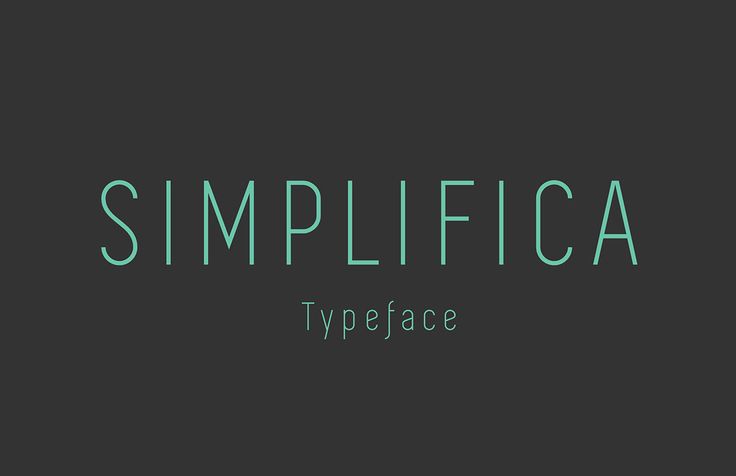
Бесплатные легкие шрифты для загрузки
В этой статье вы найдете подборку бесплатных тонких шрифтов, которые вы можете загрузить и использовать в своих проектах.
При создании дизайна вы можете передать определенное настроение или заявить о себе с помощью выбранных вами элементов дизайна, а также используемых с ними шрифтов.
Когда вы используете тонкие современные шрифты, ваш дизайн становится более привлекательным, и ваши зрители заманиваются сообщением, которое вы пытаетесь продать.
Однако у вас есть миллионы тонких шрифтов, от тонких шрифтов с засечками до тонких шрифтов без засечек, и выбор лучших тонких шрифтов для вашего конкретного проекта может стать проблемой.
В настоящее время вы заметите рост использования тонких шрифтов, и многие дизайнеры согласятся, что использование тонкого шрифта в их проекте идеально дополнит их идею.
Какие светлые или тонкие шрифты мы обсуждаем?
Основным ответом на вопрос «что такое светлый шрифт» будет шрифт, который светлее, чем римская версия шрифта, тогда как римская версия является простой, книжной или обычной.
Учитывая, что это довольно большой спектр, легким шрифтом считается тот, который использует меньший вес, чем обычный шрифт, и при неправильном использовании такой шрифт затрудняет чтение. Однако при правильном использовании это может быть очень полезно. Возможность неправильного использования отпугивает многих дизайнеров, которые предпочитают не использовать их.
Open Sans Condensed
Fonto Font Fonti Family
ARSENAL
Milano
AFTA SANS
Dosis Font Family
20020 EXISTENCE LIGHT
Quarterly BRK Font Family
CICLE
Rajdhani Font Family
RALEWAY
Web Serveroff Font Family
LANE
Labtop Font Family
ПЕЧАТЬ ЧЕТКО
Drugs Font
QUICKSAND
Tartlers End Font
WALKWAY
Fortheenas_01 Font Family
CAVIAR DREAMS
Josefin Sans Font Family
SOFIA PRO
Titillium Web Font Family
What is considered good use?
Легкий шрифт или тонкий шрифт может принести большую пользу, и вы можете получить бесплатные тонкие шрифты в Интернете, их много.
При правильном использовании они дают четкое и четкое изображение, но если не работает хотя бы одна вещь, текст довольно сложно читать, что еще хуже для потенциальных зрителей, у которых могут быть проблемы со зрением.
Плюсы использования светлых шрифтов
Светлый шрифт может обеспечить контраст, который отличает ваши заголовки от остального текста. Когда у вас нет этой дифференциации, между ними очень легко может возникнуть конфликт. Изменить размер заголовка и текста не всегда достаточно, и вам может потребоваться внести дополнительные изменения.
Здесь вступает в действие светлый шрифт, который позволяет добиться большего контраста, и читатели могут легко отличить заголовок от основного текста. Без контраста заголовки и содержание сливаются друг с другом, теряя при этом индивидуальность.
Конечно, вы можете использовать более светлый цвет текста, но что произойдет с потенциальными дальтониками, которые не видят разницы? Для подзаголовков вы можете обойтись более светлым цветом или более светлым шрифтом и улучшить разницу между тремя вещами, и вы можете регулировать контрастность настолько, насколько хотите, пока все не будет выглядеть хорошо.
Это уникальный тонкий шрифт с необычным дизайном букв. В нем представлены буквы, образованные одной линией. Шрифт имеет как прописные, так и строчные буквы.